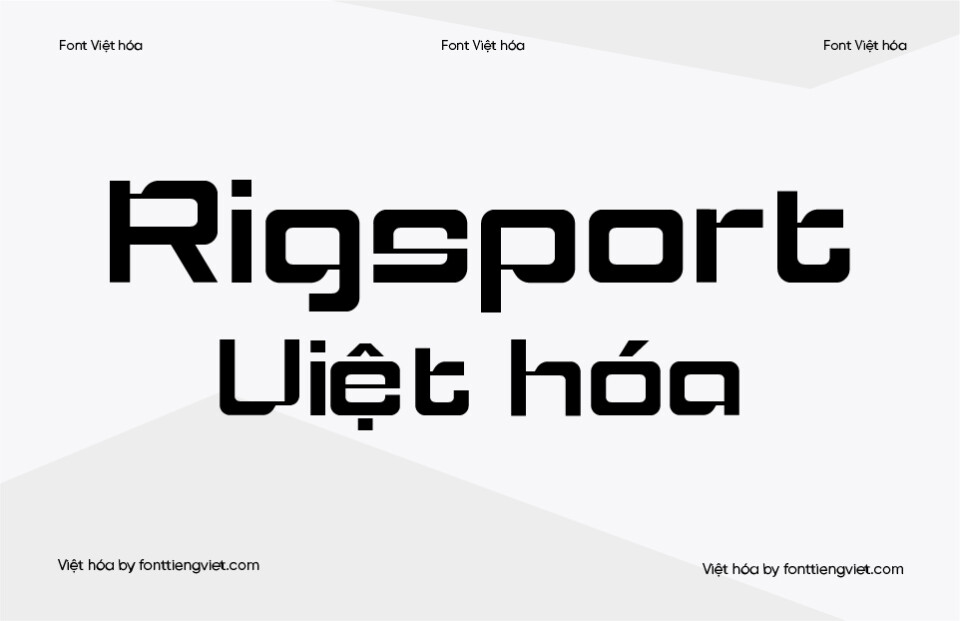
Font Việt hóa 1FTV Rigsport
Giới thiệu về Font Việt hóa 1FTV Rigsport
Trong thế giới đồ họa hiện đại, việc lựa chọn một bộ Font Miễn Phí chất lượng đóng vai trò then chốt tạo nên linh hồn cho tác phẩm. Font Việt hóa 1FTV Rigsport là một trong những lựa chọn hàng đầu cho những ai đang tìm kiếm phong cách mạnh mẽ, chuyên nghiệp. Được lấy cảm hứng từ tinh thần thể thao sôi động, bộ font này mang đến những đường nét dứt khoát, góc cạnh và tràn đầy năng lượng. Phiên bản Việt hóa giúp các nhà thiết kế tại Việt Nam dễ dàng ứng dụng vào các sản phẩm truyền thông mà không lo lỗi hiển thị dấu câu.
Đặc điểm nổi bật của Font Việt hóa 1FTV Rigsport
Bộ font này nổi bật với cấu trúc dày dặn, các ký tự được thiết kế theo dạng khối vuông vức, gợi liên tưởng đến các số áo thi đấu hay logo của các câu lạc bộ bóng đá nổi tiếng. Font Việt hóa 1FTV Rigsport cực kỳ phù hợp cho các tiêu đề lớn, banner quảng cáo sự kiện thể thao hoặc làm nội dung trên các nền tảng mạng xã hội. Khả năng đọc hiểu tốt ở khoảng cách xa giúp font chữ này trở thành công cụ đắc lực cho các chiến dịch marketing ngoài trời.
Cách ứng dụng Font Việt hóa 1FTV Rigsport hiệu quả
Để tận dụng tối đa vẻ đẹp của bộ font này, bạn nên kết hợp nó với các gam màu tương phản mạnh như đỏ, đen hoặc xanh dương đậm. Đối với các bạn học sinh hoặc sinh viên, việc sử dụng font chữ này trong các bài thuyết trình về giáo dục thể chất hay dự án ngoại khóa sẽ tạo ấn tượng thị giác cực kỳ chuyên nghiệp. Đừng quên căn chỉnh khoảng cách giữa các chữ cái để đảm bảo sự cân đối cho bố cục tổng thể.